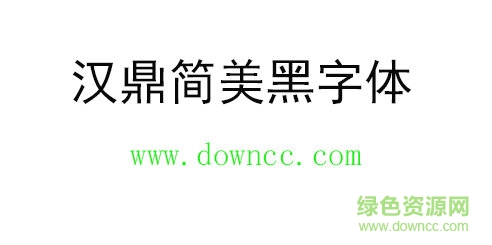
漢鼎簡(jiǎn)美黑是一款非常漂亮的簡(jiǎn)體字體,該字體比較簡(jiǎn)單,纖細(xì),非常不美觀,一般只有在特殊的新聞界面才會(huì)看得見(jiàn),大多數(shù)都是混雜起來(lái)使用的,這樣也能提升界面的整體美觀度,喜歡的朋友趕緊來(lái)綠色資源網(wǎng)下載吧!